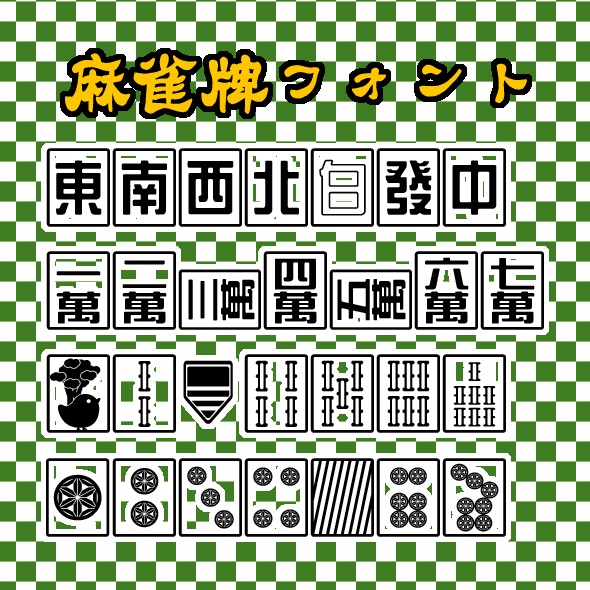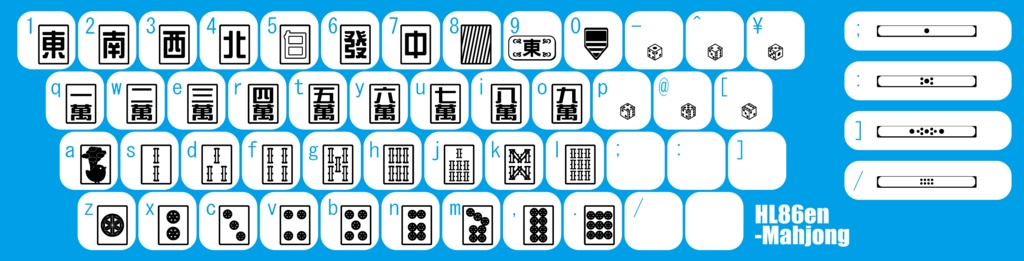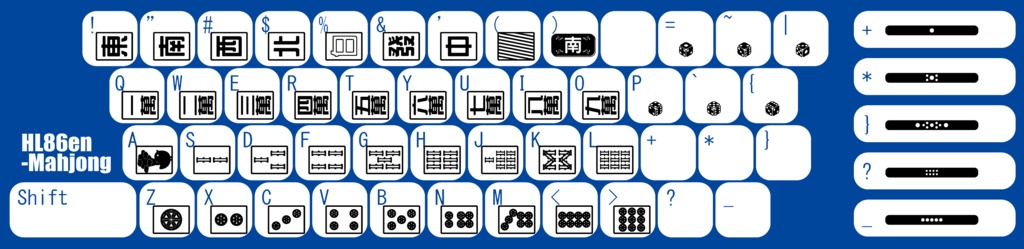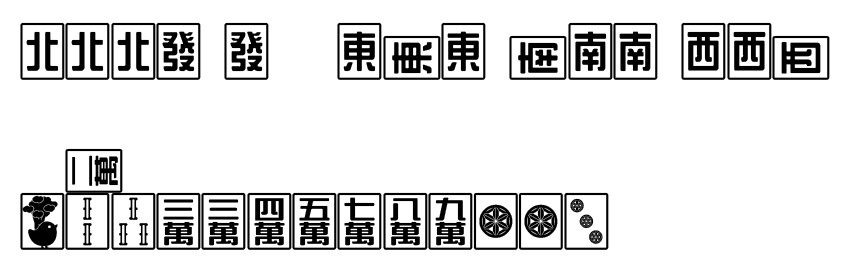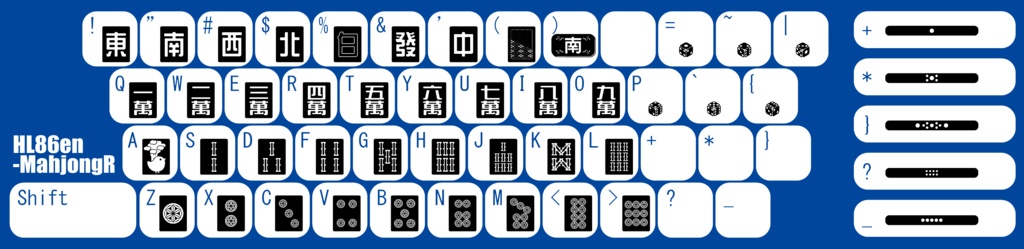
Wingdingsフォントのように文字ではなく麻雀牌が入ったパイフォント(ttf)です。 字牌、萬子、索子、筒子、起家マーク、サイコロ、点棒が入っています。(キーの総数の関係で白抜き500点棒はありません) Shift+で牌が横向きになります。詳しくはサンプル画像をご覧いただければ。(zip内にも一覧を同梱) ※24/09/08追記 「横向きいらねえんじゃねえか?」ということで+Shiftを反転色にしたHL86en-MahjongRを作ったので置いておきます。 配列は同じで柄は背面だけ変えてあります。(サンプル画像5枚目)